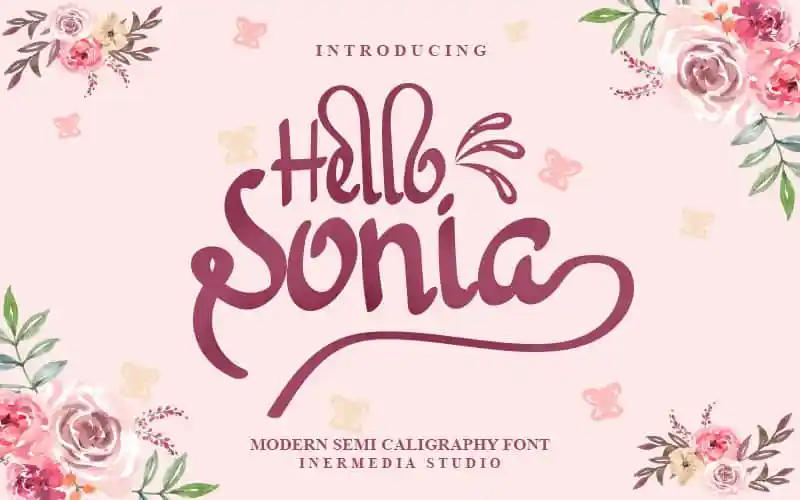
Hello Sonia Script Font – Download Grátis
A fonte ‘Hello Sonia Script Font’ é uma escolha perfeita para quem busca uma escrita elegante e moderna. Desenvolvida pelo inermediaSTUDIO, essa fonte manterá sua estética sofisticada do papel enquanto se mantém atual e fresca. Seu uso versátil será adorado por criadores de conteúdo, desde a criação de cartões de visita e títulos até o design de materiais de escritório. Agradável para designers gráficos, ‘Hello Sonia Script Font’ é uma fonte que fará sua marca se destacar. Além disso, seu uso em diferentes ambientes de trabalho permitirá que você atenda a um público amplo com um estilo inovador e encantador.